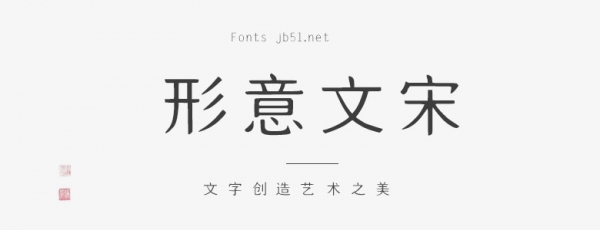
形意文宋由深圳形意設(shè)計(jì)通過(guò)字體家AI生成字體,形意文宋永久免費(fèi)商用,具體免費(fèi)商用授權(quán)范圍請(qǐng)咨詢深圳形意設(shè)計(jì)官方,適合應(yīng)用于平面宣傳設(shè)計(jì)、網(wǎng)頁(yè)設(shè)計(jì),書(shū)法字帖等領(lǐng)域。